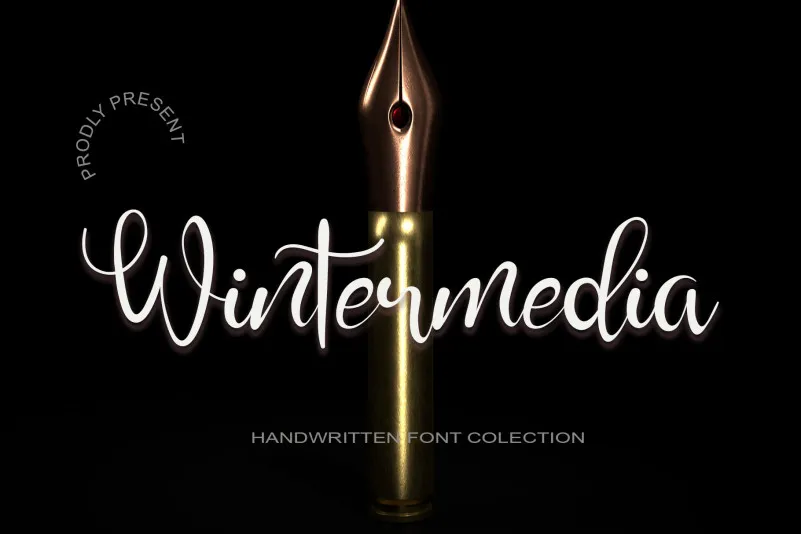
Wintermedia Font – Fonte Grátis
Wintermedia Font
A fonte ‘Wintermedia Font’ é perfeita para quem busca uma mão escrita suave e elegante. Esta font se destaca pelo seu toque especial, oferecendo um ar pessoal que enriquece qualquer projeto gráfico. É ideal para diversas aplicações visuais, desde pequenos detalhes até designs de grande porte. Se apaixone por sua versatilidade e descubra inúmeras maneiras criativas de utilizá-la. Utilize-a para criar projetos realmente impressionantes. A ‘Wintermedia Font’ do designer kateengciu é uma escolha ótima para quem procura um estilo único e sofisticado que se adapta a qualquer tipo de design, tornando-o ainda mais especial.